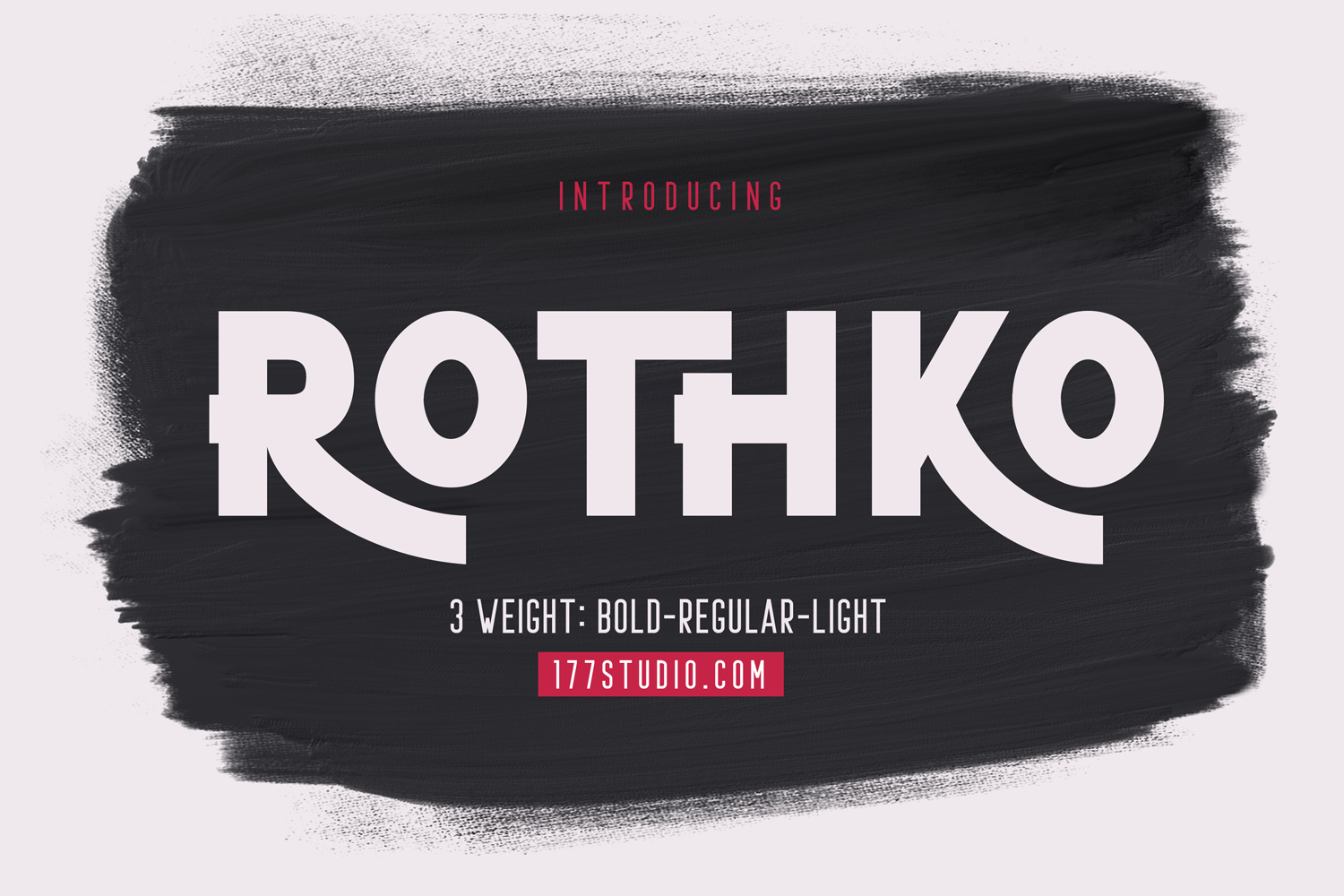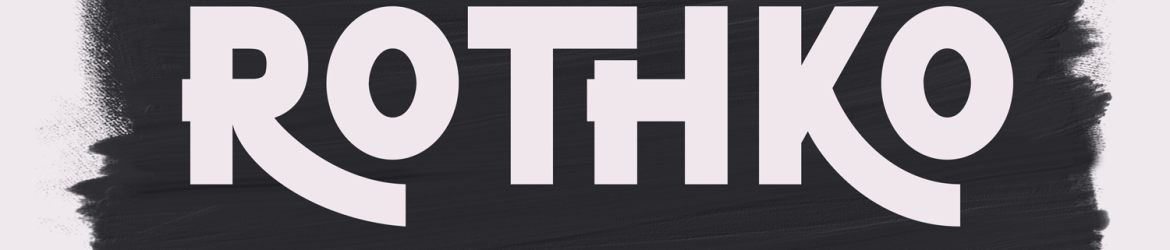
Rothko Font – Download Grátis
A Rothko Sans Serif é uma fonte sem serif moderna desenvolvida pela 177Studio que combina a simplicidade elegante dos tipos geométricos com as linhas leves e estilizadas do sans-serif. Esse é um belo tipo de texto para usar em títulos e parágrafos, especialmente quando você precisa de uma aparência confortável ao ler, enquanto mantém sua identidade única, simples e elegante. Perfeita tanto para textos robustos que podem ser usados nos displays quanto para criações branding, anúncios, folhas de propaganda, banners, embalagens, capas de revistas, websites, design de logotipos e muito mais. Este tipo é ideal para qualquer projeto de design que necessite de uma tipografia moderna e limpa. A Rothko Sans Serif não apenas oferece aparência atraente e fácil de ler, mas também adiciona um toque único à sua próxima peça de design. É um ótimo exemplo de como um tipo simples e elegante pode transformar o aspecto de seus projetos.